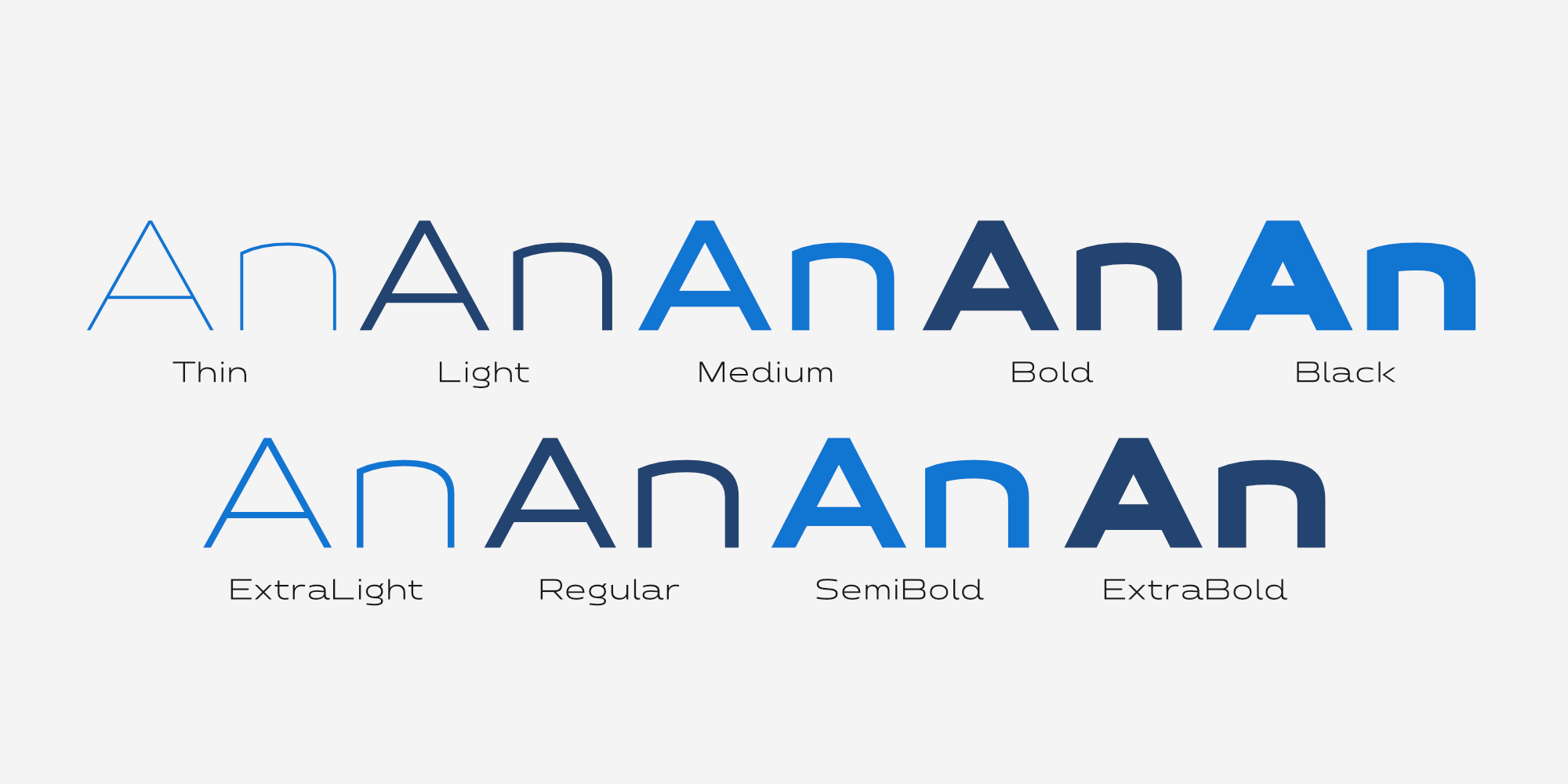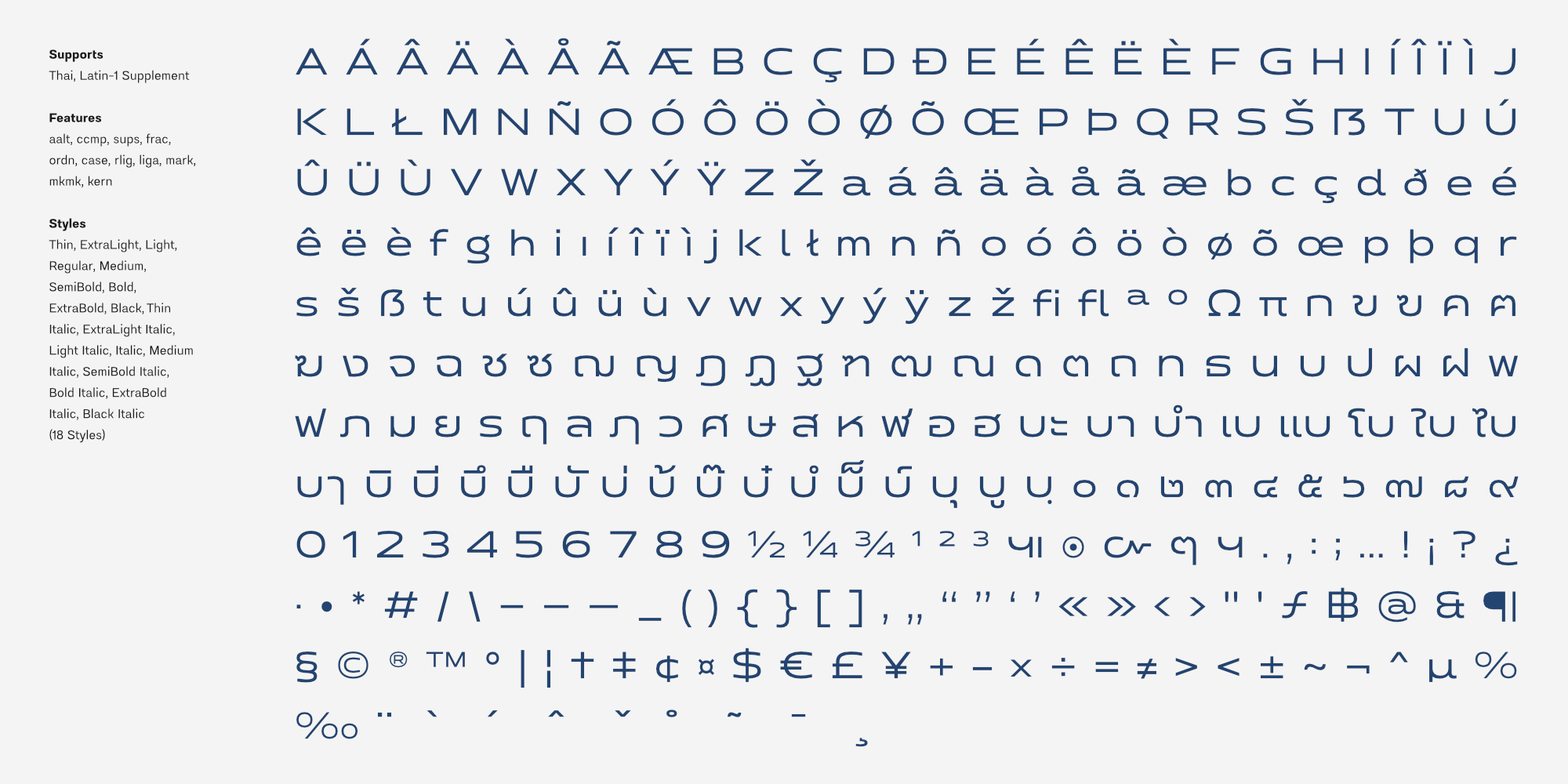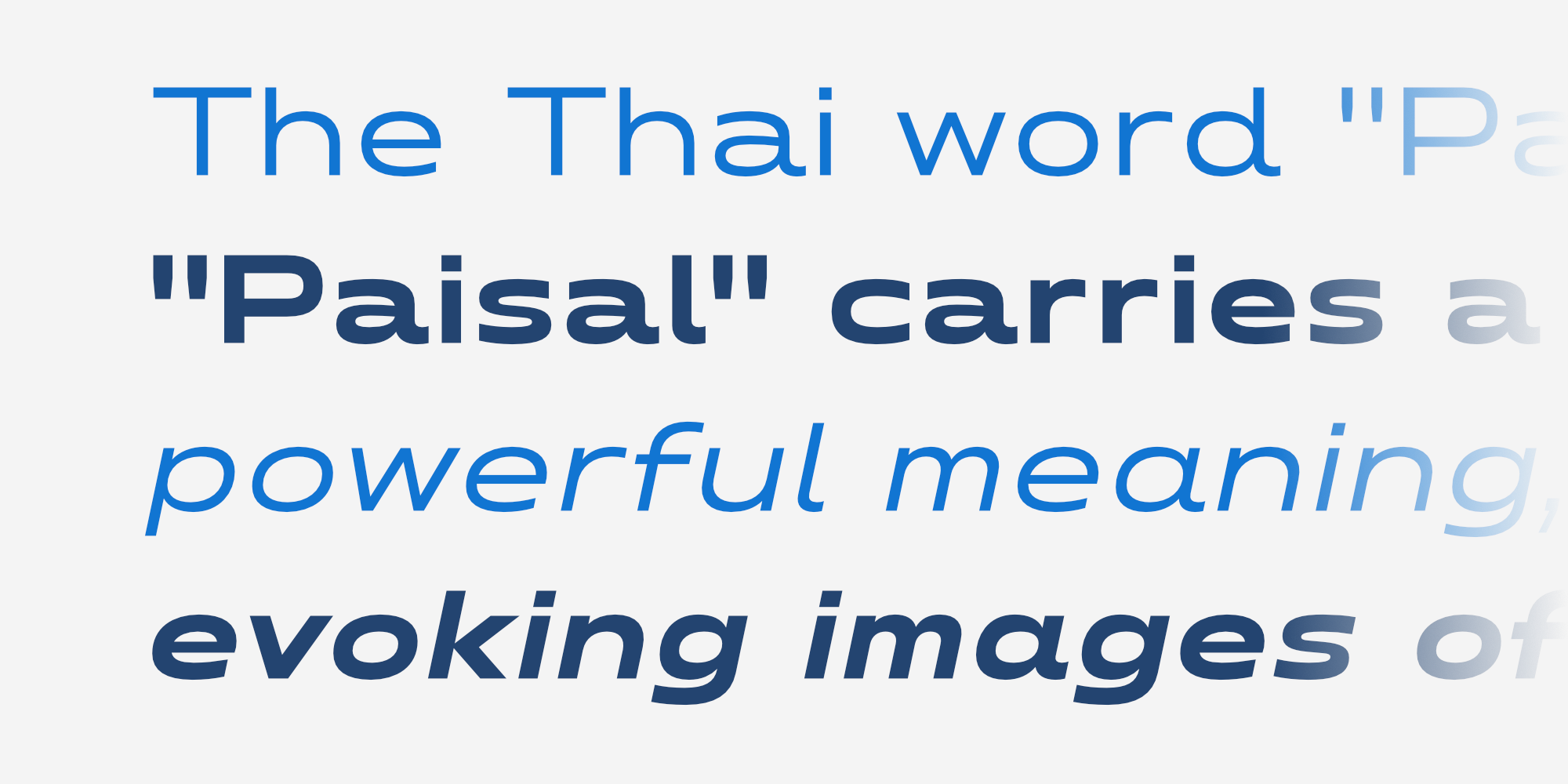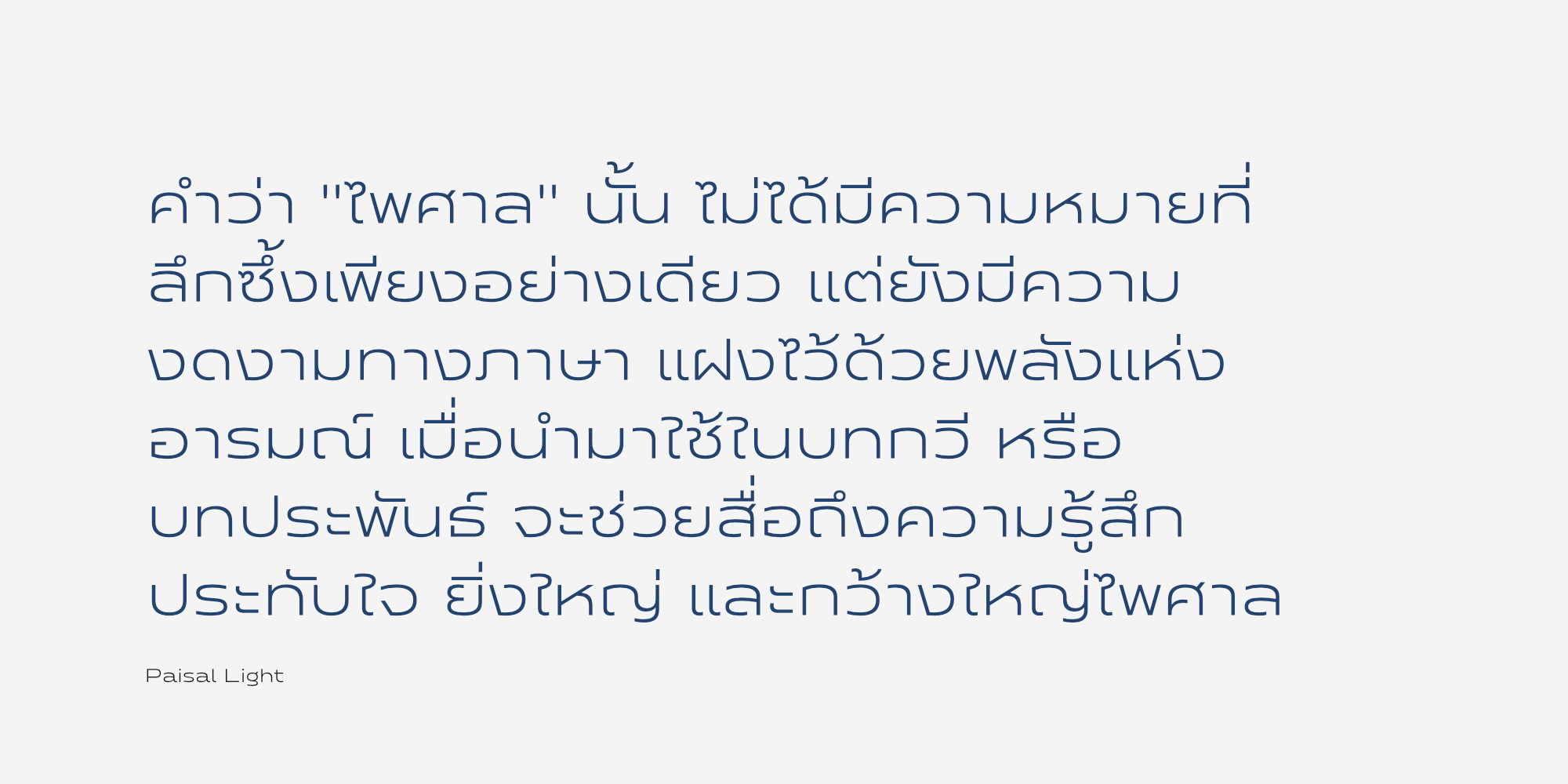
ไพศาล | Paisal
ชื่อฟอนต์ : ไพศาล | Paisal
Paisal เป็นแบบอักษรไร้เชิงที่มีความกว้างมากกว่าปกติเมื่อเทียบกับผลงานก่อนหน้าของ Jipatype โดยได้รับการออกแบบให้มีภาพลักษณ์โดยรวมที่เรียบง่ายและทันสมัย แบบอักษรนี้ประกอบด้วย 18 รูปแบบ ครอบคลุมตั้งแต่น้ำหนักบางที่สุดไปจนถึงหนาที่สุด โดยรองรับทั้งชุดอักขระลาติน 1 และอักขระไทย
Paisal มีความเหมาะสมสำหรับการใช้งานในสิ่งพิมพ์ต่าง ๆ ทั้งในรูปแบบดิจิทัลและสื่อสิ่งพิมพ์ทั่วไป อีกทั้งยังสามารถนำไปประยุกต์ใช้ในงานออกแบบหลากหลายประเภท อาทิ ป้ายโฆษณา ข้อความพาดหัว และงานออกแบบอื่น ๆ